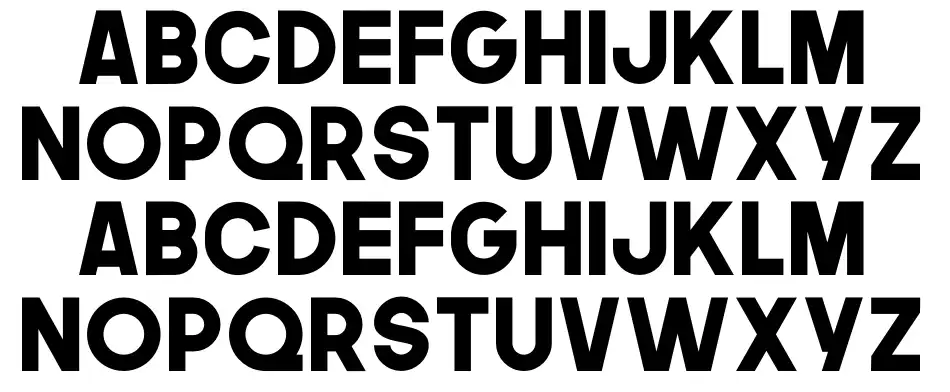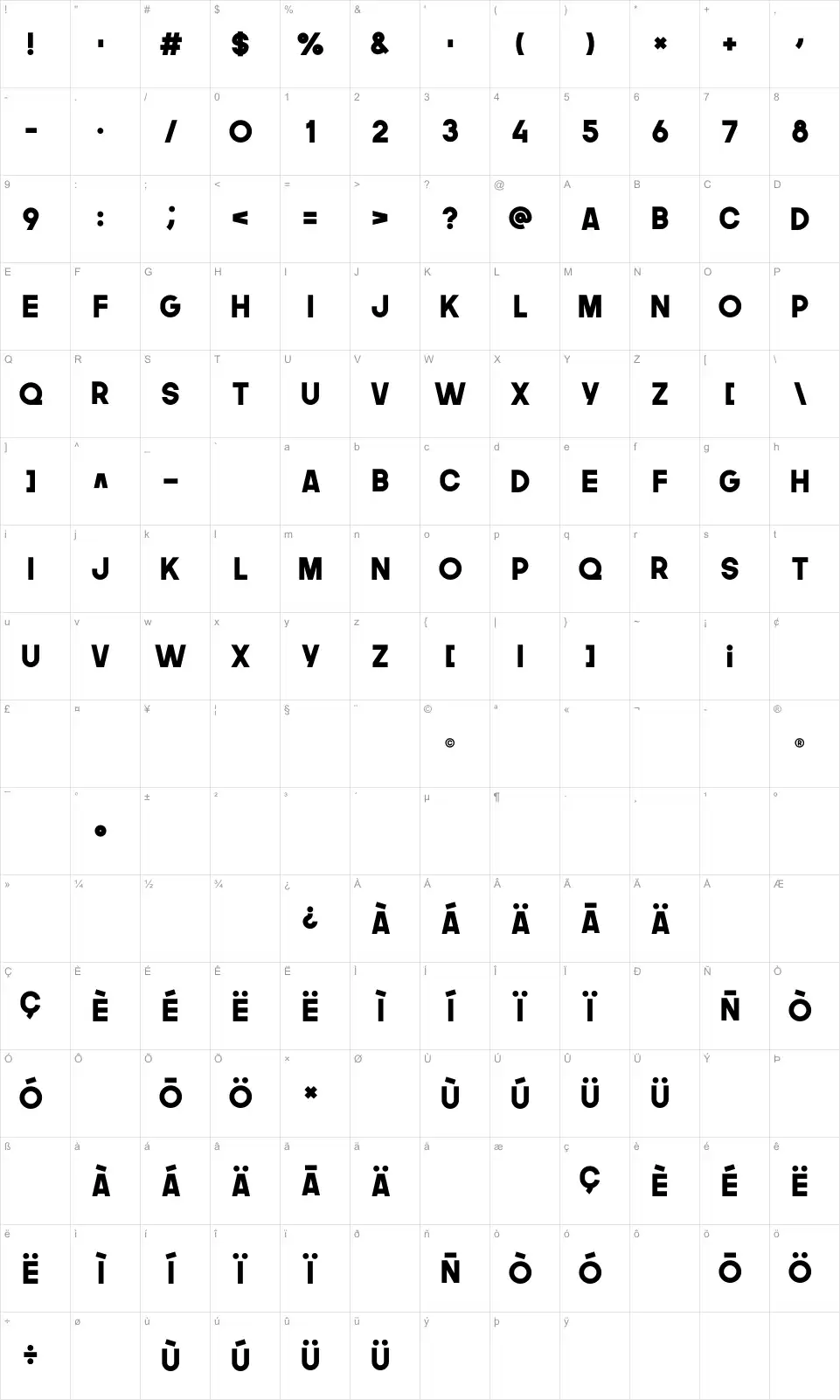
A fonte The Next Font é uma escolha ótima para quem busca uma tipografia minimalista e elegante. Incluída na categoria de Sans Serif, ela se destaca com sua forma simples e limpa, que combina perfeitamente com projetos de design básico. Se você está buscando uma fonte para projetos de texto ou para criar layouts minimalistas, The Next Font pode ser o ideal. Possui uma licença gratuita, o que a torna uma opção atraente para projetos de uso pessoal e até mesmo comerciais. Adicionada em julho de 2022, já foram feitos 2612 downloads, o que demonstra seu sucesso e popularidade. Com seu tamanho de 14 KB, é uma opção leve e conveniente para qualquer projeto. Experimente a fonte e veja como ela se ajusta ao seu projeto. Descarregue-a ou gera uma pré-visualização de texto personalizada online para ver como ela ficará antes de começar a usá-la.